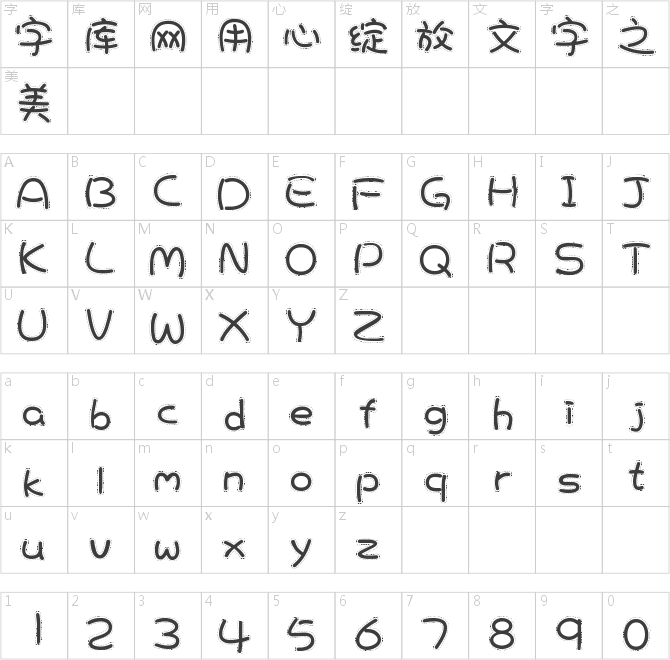
字魂224號-光點浣熊體
字魂224號-光點浣熊體是一款創意衍生字。字體的折筆處以圓代方,變口為圓,字體的輪廓加入了白色虛線的設計,字的趣味性十足,適用于兒童書刊、海報、招牌等應用場景。
字魂224號-光點浣熊體字體zihun224hao-guangdianhuanxiongti字庫是一款讓人賞心悅目、百看不厭的中文字體,適合各類廣告和產品包裝設計應用,字體大小25.63MB,格式為ttf字體,上傳用戶是徐明澤,作者/版權方為字魂